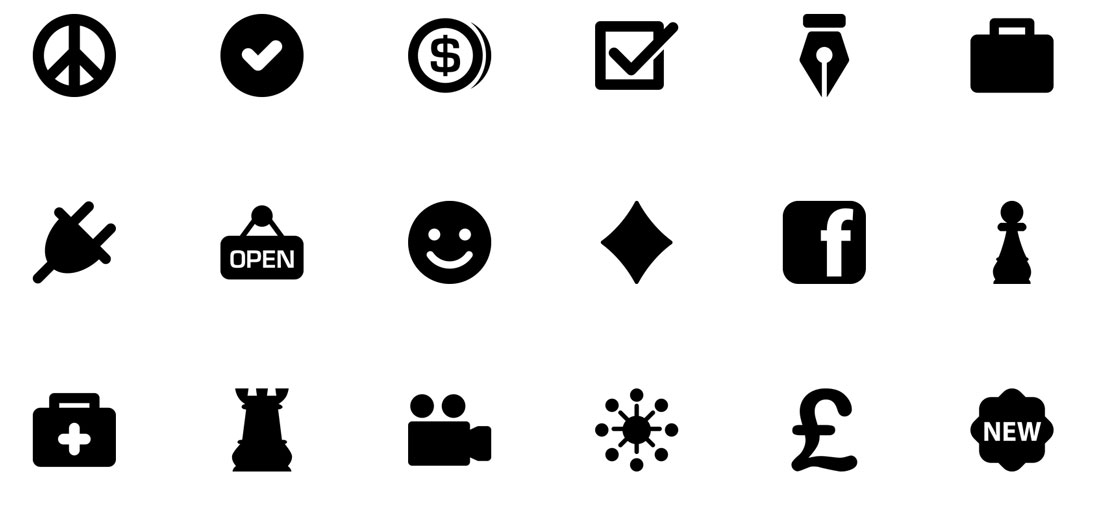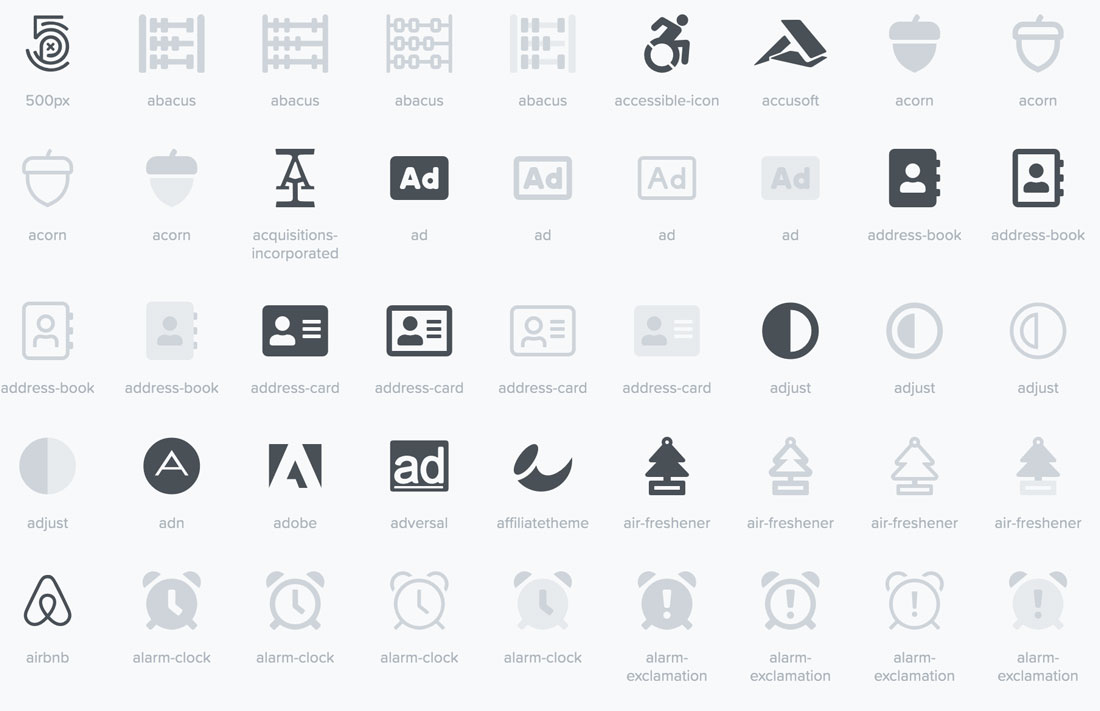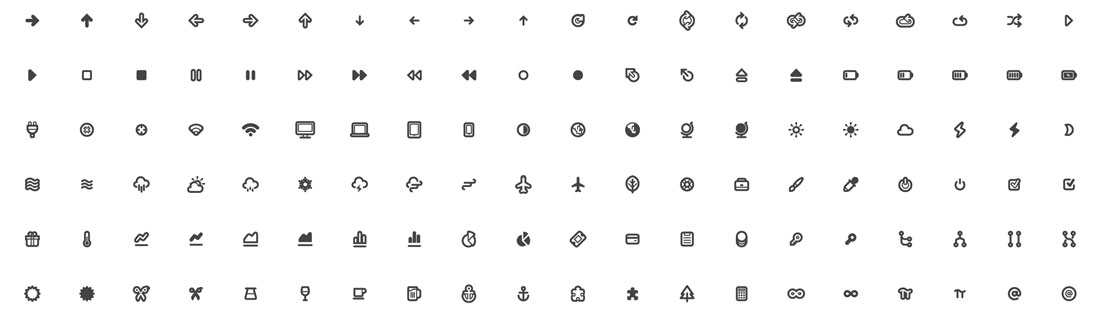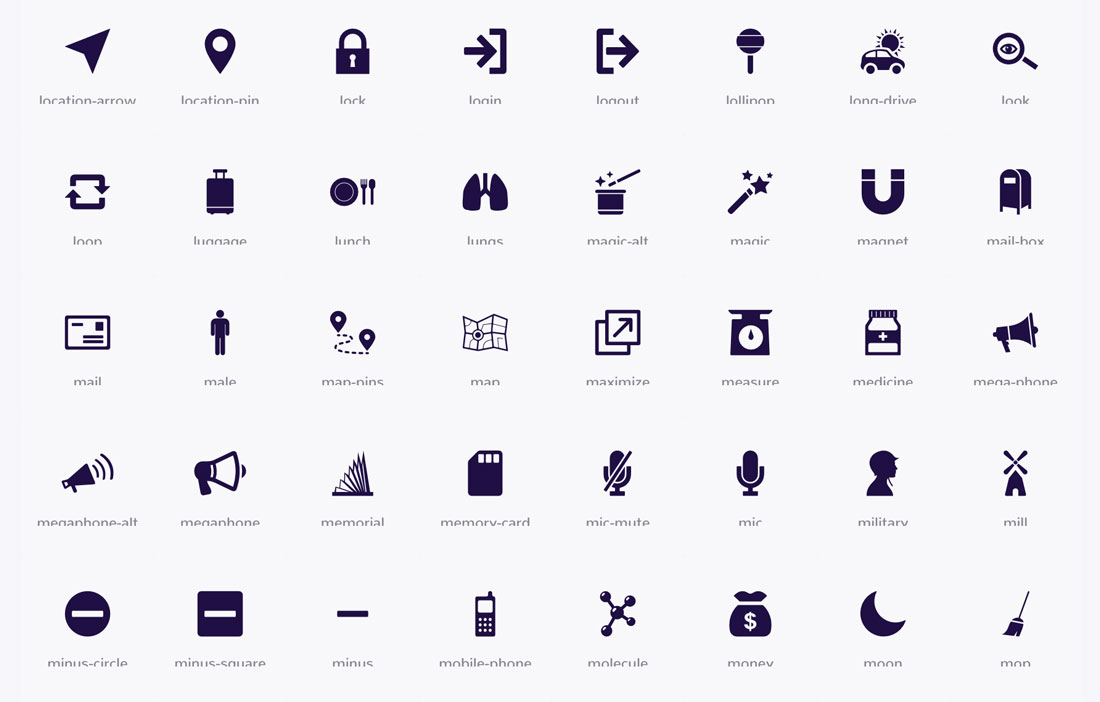
圖標字體現(xiàn)在是常見CSS問題的流行解決方案,如何以高效,快速的方式將圖標整合到你的網(wǎng)站設計中。
目前互聯(lián)網(wǎng)上已經(jīng)有很多的服務或者資源提供,借助這些,你可以輕松選擇和使用圖標字體,而無需從頭開始創(chuàng)建自己的圖標。
但是圖標字體到底是什么以及如何使用它們? 這是你需要了解的有關圖標字體的所有內(nèi)容的指南。
什么是圖標字體?(What Is an Icon Font?)
圖標字體是使用微小圖像而不是字母形式的字體。 與字符一樣,每個圖標字體都是矢量元素,可根據(jù)需要進行伸縮,并可以使用CSS樣式進行修改。
使用圖標字體的主要原因是你可以輕松更改大小,顏色,形狀。 圖標字體本質上是透明的,因此你可以將它們放在任何顏色或類型的背景上,還可以添加筆觸或更改圖標的不透明度。
所有的設置操作均可以使用CSS完成,因此你不必為設計中的每個新圖標實例創(chuàng)建唯一的圖像(這對于保持網(wǎng)站設計和代碼的輕量級非常有用)。
圖標字體是矢量圖像,這意味著它們是可隨意進行縮放而不失真的。 與其他字體一樣,你可以根據(jù)需要將它們設置更大或更小。 僅將圖標字體用作藝術元素,甚至在其他文本字段中。
使用圖標字體的優(yōu)缺點(Pros and Cons of Using Icon Fonts)
那么,為什么要使用(或避免使用)圖標字體? 以下是使用這種風格的藝術元素的一些利弊。
1.使用圖標字體的優(yōu)勢
· 只要CSS中存在相應的類,圖標就易于縮放;
· 你可以在互聯(lián)網(wǎng)上輕松獲得既有的大型圖標庫;
· 更改圖標屬性非常容易,無論你使用什么來構建網(wǎng)站的;
· 將圖標添加到網(wǎng)站設計上的任何頁面都很容易(只需插入圖標名稱);
· 有數(shù)千種各種樣式的圖標可供選擇;
· 如果需要更高的自定義,你甚至可以創(chuàng)建自己的圖標字體。
2.使用圖標字體的劣勢
· 圖標是單色或漸變色(在大多數(shù)情況下,不過一些可以提供更多自定義選項的服務正在改變這一點);
· 如果無法加載到圖標字體,則沒有其他的備用字體供使用;
· 你可能不需要完整的圖標集;
· 一些瀏覽器器還不能或不完全支持圖標字體;
· 你可能找不到適合你的需求的資源。
如何使用圖標字體(How to Use Icon Fonts)
雖然根據(jù)所選擇的程序或服務的不同,使用圖標字體的規(guī)則或注意事項可能會略有不同,但基本思路是相同的。
通常,你有三個選擇(除非你打算自己做一些編碼調整):
· 使用可以安裝所有內(nèi)容的插件,因此你只需要調用要使用的圖標即可(超級簡單?。?。
· 使用CMS或網(wǎng)站構建器中的內(nèi)置字體圖標。 如果你沒有自定義網(wǎng)站或需要特定類型的字體圖標,則此方法非常有用。 大多數(shù)網(wǎng)站構建器都提供相關的服務和功能模塊。
· 手動鏈接到外部的圖標字體。
使用圖標字體還是SVG格式文件?(Icon Fonts vs. SVGs)
目前面臨的最大的爭議可能是你是否(或想要)使用圖標字體而不是SVG圖像,以便在你的網(wǎng)站設計中插入圖標。 兩種選擇都同樣可行,并且與個人喜好有很大關系。
SVG(可縮放矢量格式)文件可為你提供更多的設計靈活性(不僅限于一種顏色)。 可擴展的小型文件可以直接上傳到你的媒體目錄中,并且易于使用。 如果你只需要少量圖標并且不想處理庫,那么這是一個不錯的選擇。
SVG格式支持添加更多顏色和動畫的能力,因此更加靈活。
從長遠來看,圖標字體可能在加載速度上更快,因為它們已被緩存,但是差異上可能很?。⊿VG格式文件在大小上一般都很小)。
定位圖標字體可能會有些棘手,因為它們要遵循典型的字體規(guī)則,例如大小,行距和垂直對齊。 僅這就是為什么大多數(shù)使用圖標字體的人更多選擇一家既有的提供商而不是嘗試自己做的原因。
SVG可以包含alt元素,這些元素使它們比圖標字體更易于訪問,而圖標字體可以作為字母字符出現(xiàn)在屏幕閱讀器上。
圖標字體通常使大多數(shù)人更容易找到和使用,字體庫通常都是可用的,并不難理解。 想要更多設計控制和自定義選項的用戶一般首選SVG圖標。
這兩個選項都是常用的,并且在大多數(shù)情況下效果都很好。 你所需要做的就是選擇一個你最喜歡的以及與你的設計和用戶界面相匹配的選項。
總結
圖標字體如此受歡迎的原因之一是它們用途廣泛且易于使用。 借助可擴展的格式,只需單擊幾下即可將其安裝到大多數(shù)項目中,幾乎任何人都可以快速開始使用圖標字體。
圖標字體的最大的優(yōu)勢是元素使用CSS,而不是獨立的圖像文件。 這對于創(chuàng)建一個精簡的網(wǎng)頁設計非常有用,該網(wǎng)站具有可以快速加載的矢量格式元素(如果以后需要更改大小,則非常有用)。